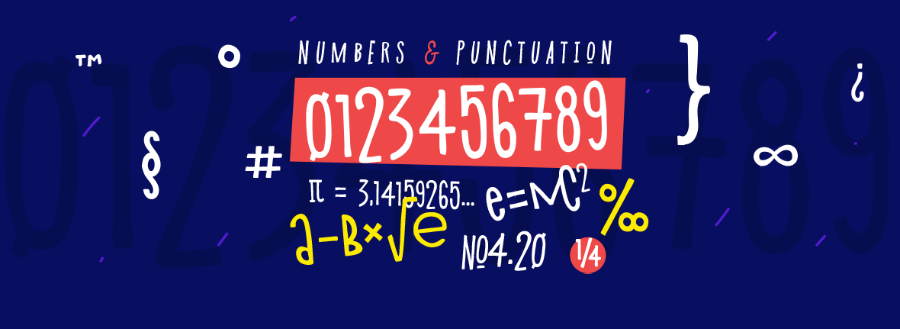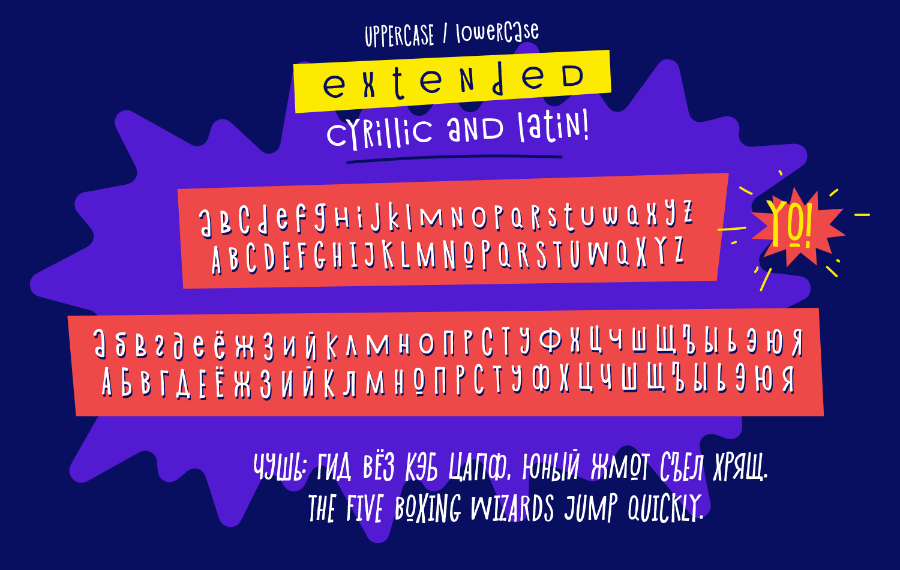
Shnobel显示免费字体
Shnobel 显示自由字体是一组两个字体,来自Shnobel的一个名字,一个意第绪语的字,在俄罗斯俚语意思是一个有趣的大鼻子!这种字体是一个非常情绪化,令人兴奋,奇怪,狂野,有趣,非凡。 Shnobel适用于不同的设计目的。此外,它还为您提供连字和替代字形,使Shnobel更加狂野!另外,超级拉丁&西里尔文,以及各种格式的600多个glifs。